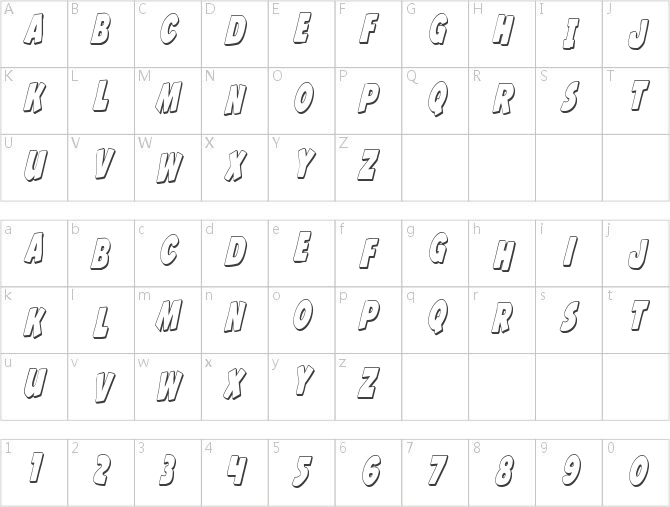
jcandlestick3dextracond
jcandlestick3dextracond字體字庫是一款讓人賞心悅目、百看不厭的英文字體,適合各類廣告和產(chǎn)品包裝設(shè)計(jì)應(yīng)用,字體大小0.13MB,格式為ttf字體,上傳用戶是1733150348,作者/版權(quán)方為未知